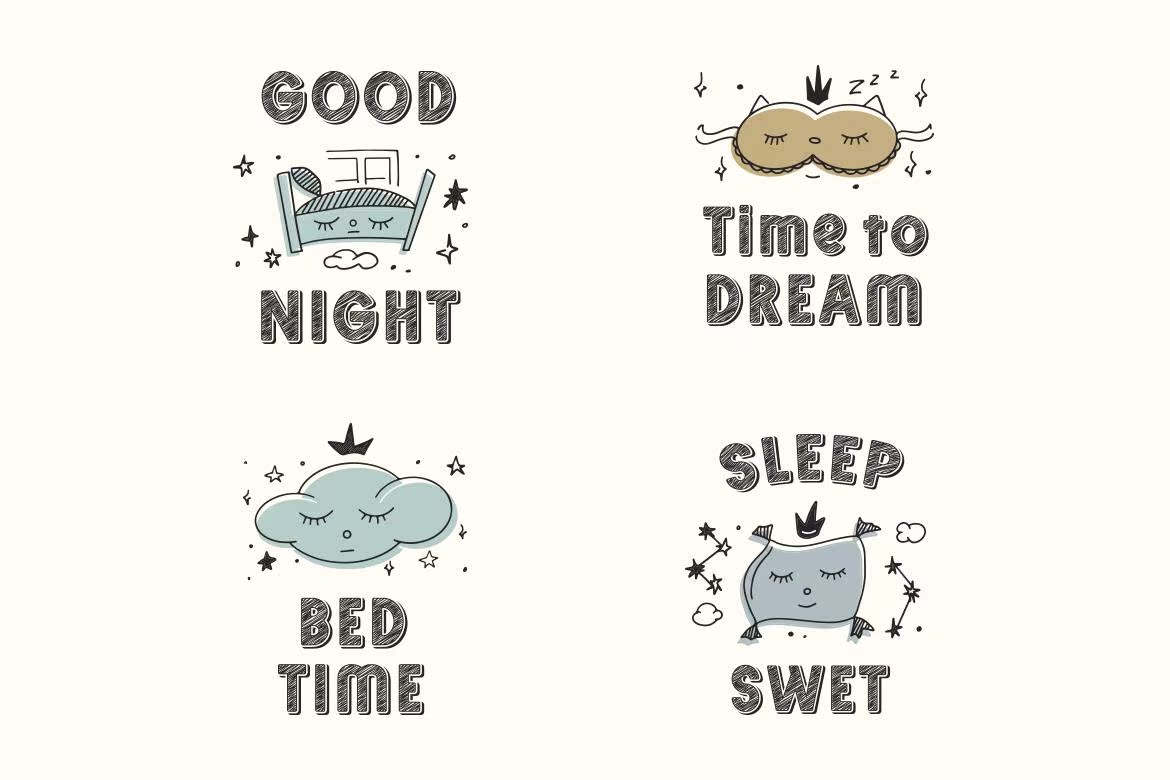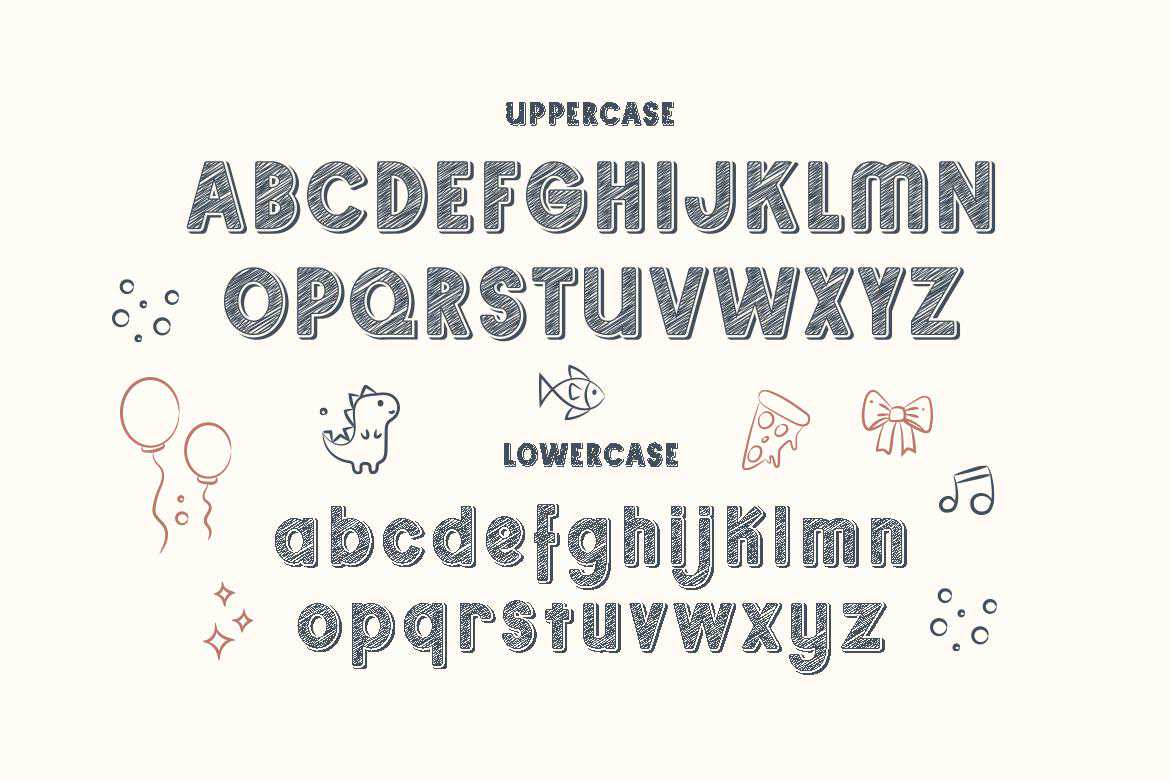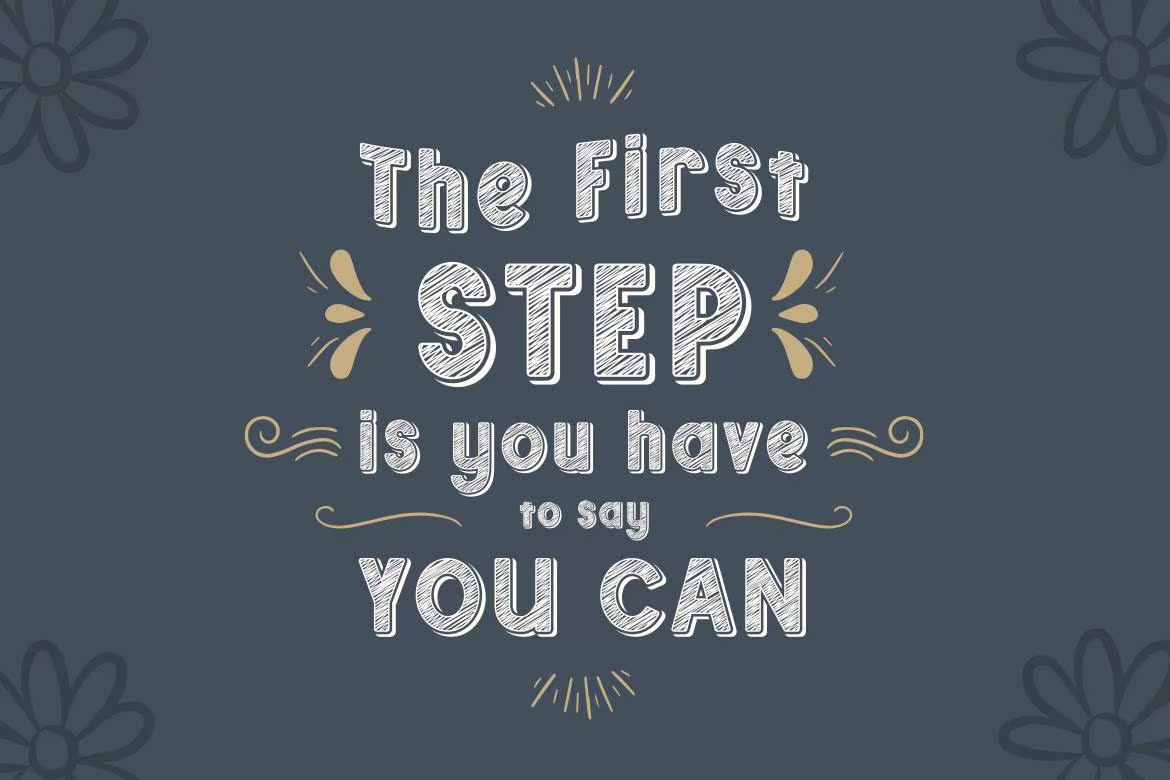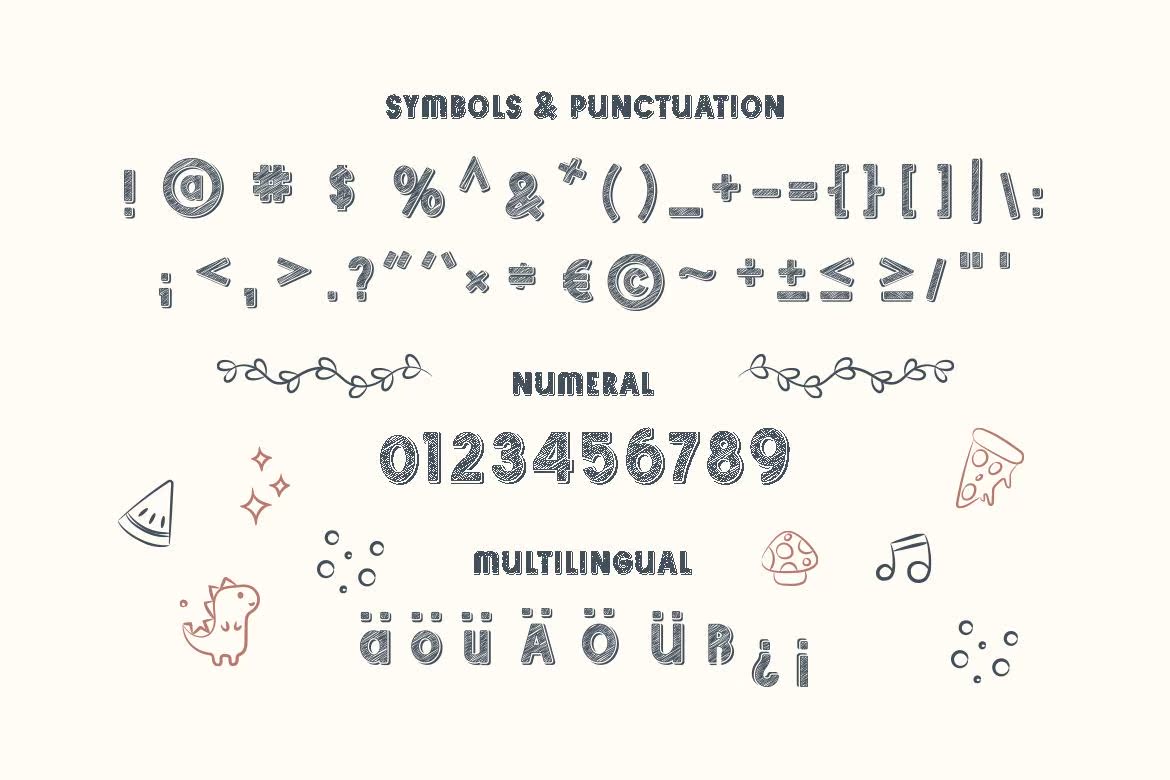
Sketchupisa以一种令人信服的魅力展示了Font。从它的异想天开的感觉中获得灵感,并将任何有创意的项目变成一个抢眼者!完美搭配派对活力、打印报价、立式包装或休闲T恤!您甚至可以使用它来创建令人惊叹的标题、徽标、菜单和社交媒体。此外,您还可以使用它来创建主题!完整版本下载:Sketchupisa Display Font具有令人信服的魅力。受其异想天开的感觉启发,并将任何创意项目变成一个Yecatcher!完美搭配派对活力、打印报价、立式包装或休闲T恤!您甚至可以使用它来创建令人惊叹的标题、徽标、菜单和社交媒体。此外,您还可以使用它来创建主题!FullVersionDownloadHere: